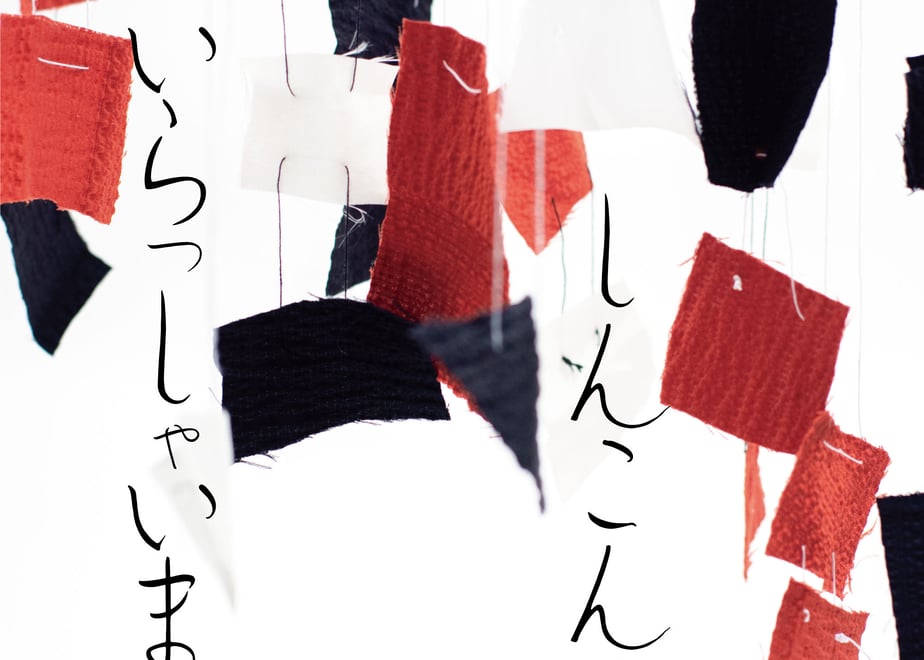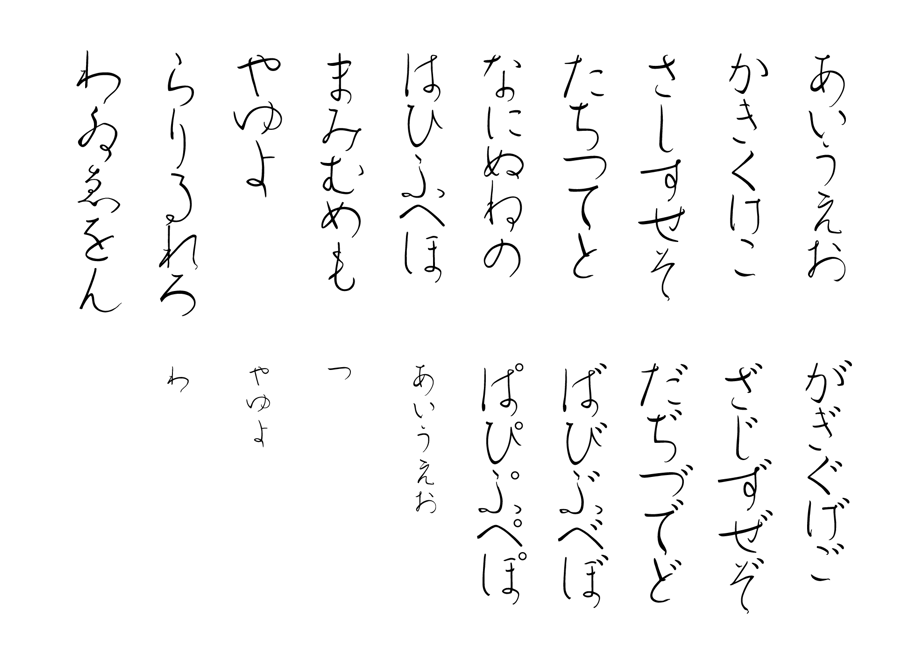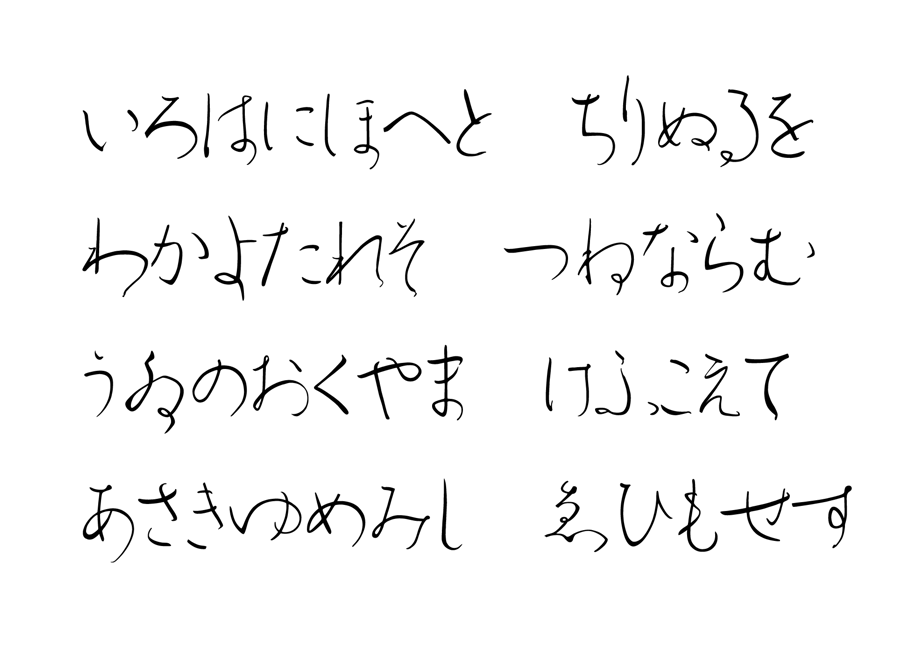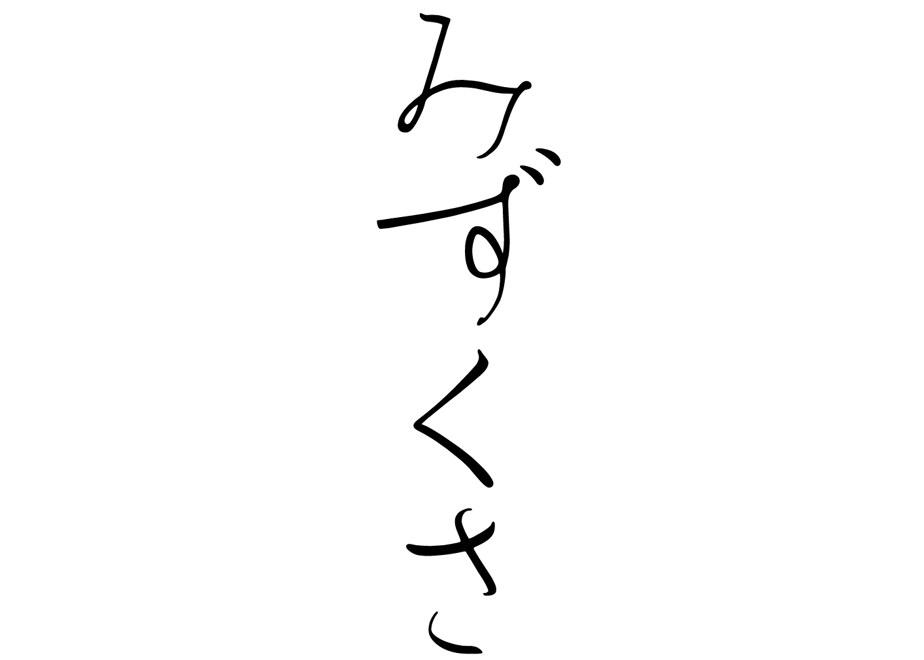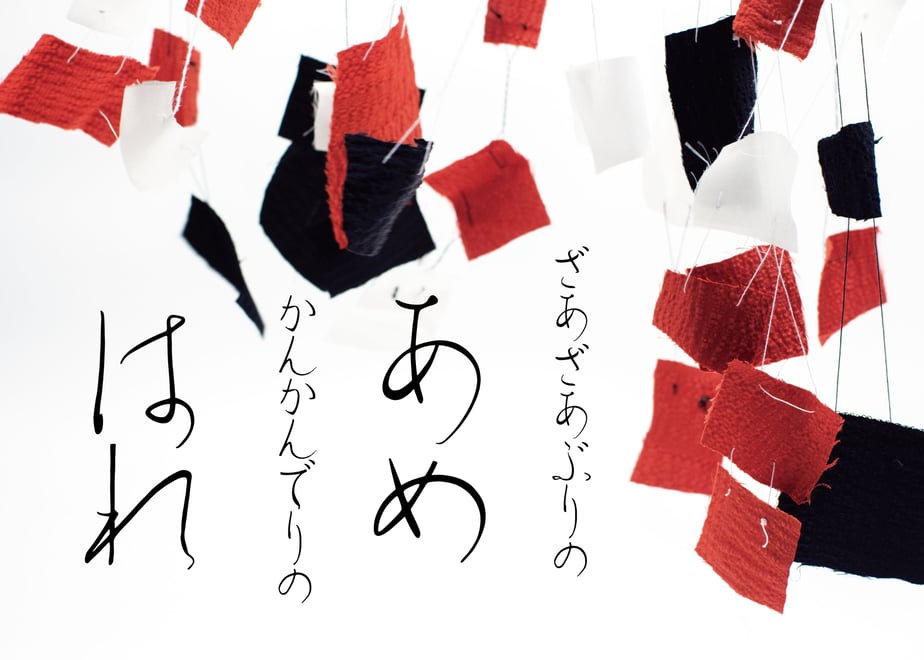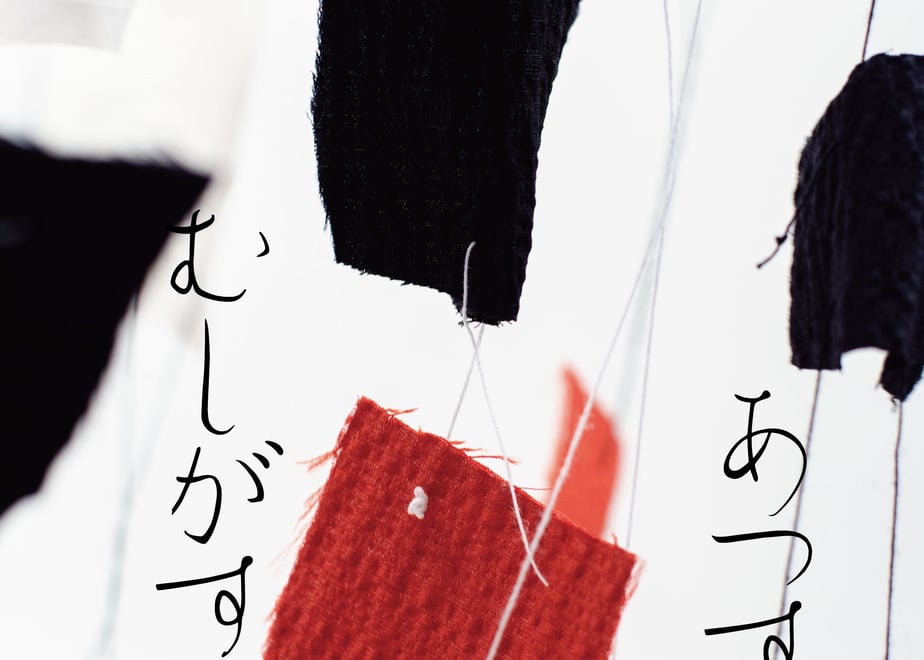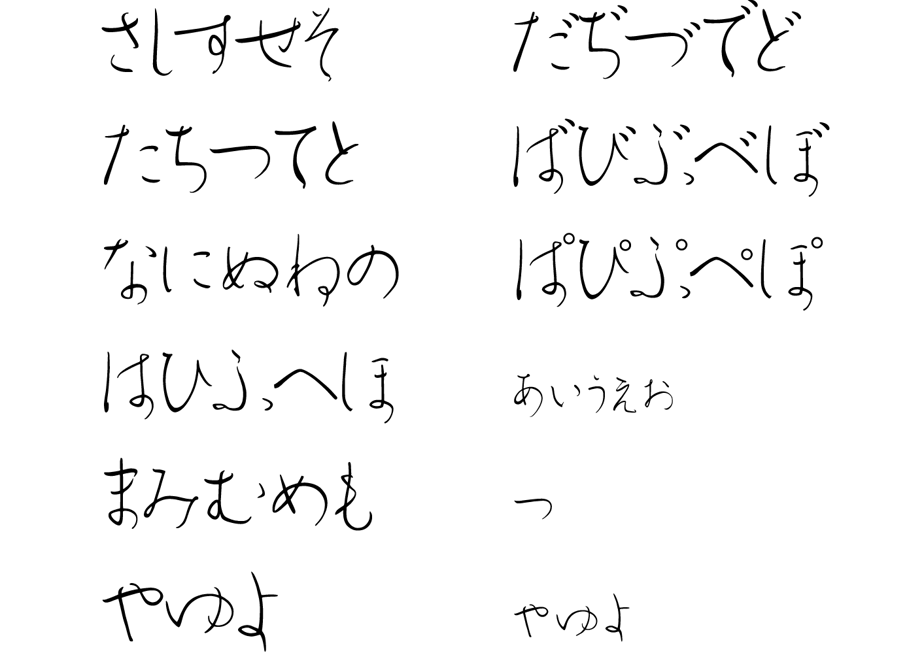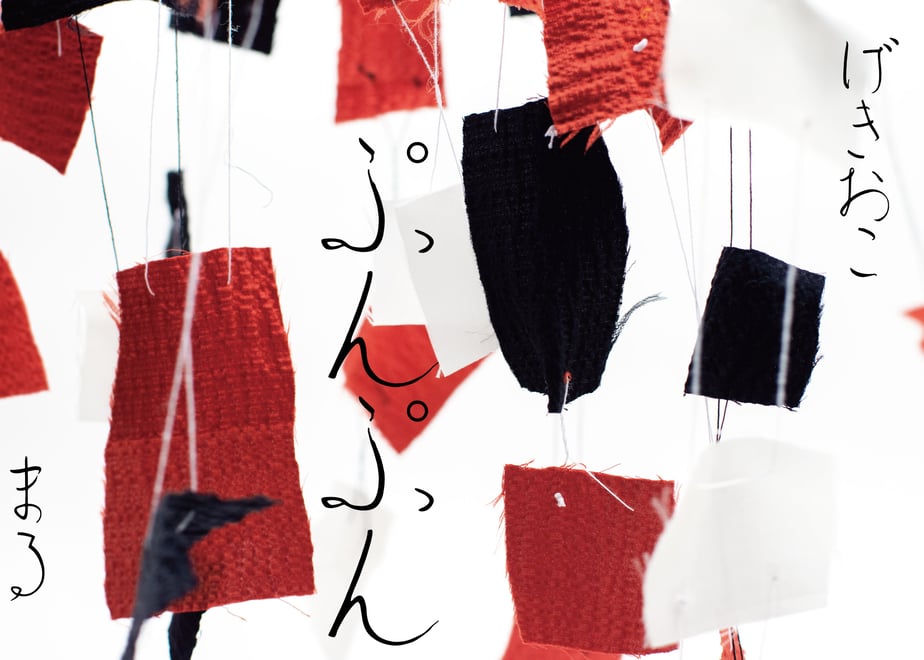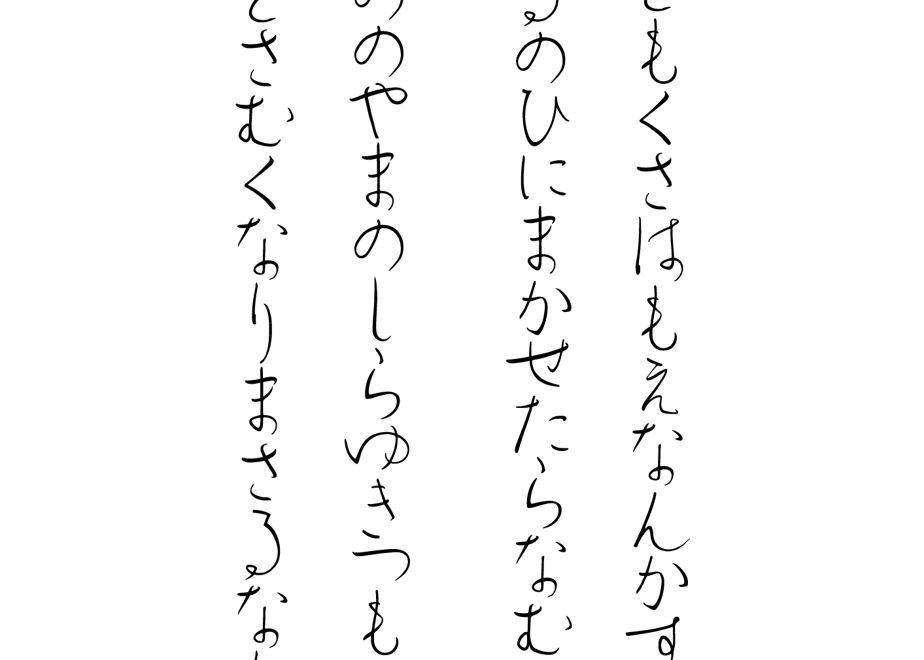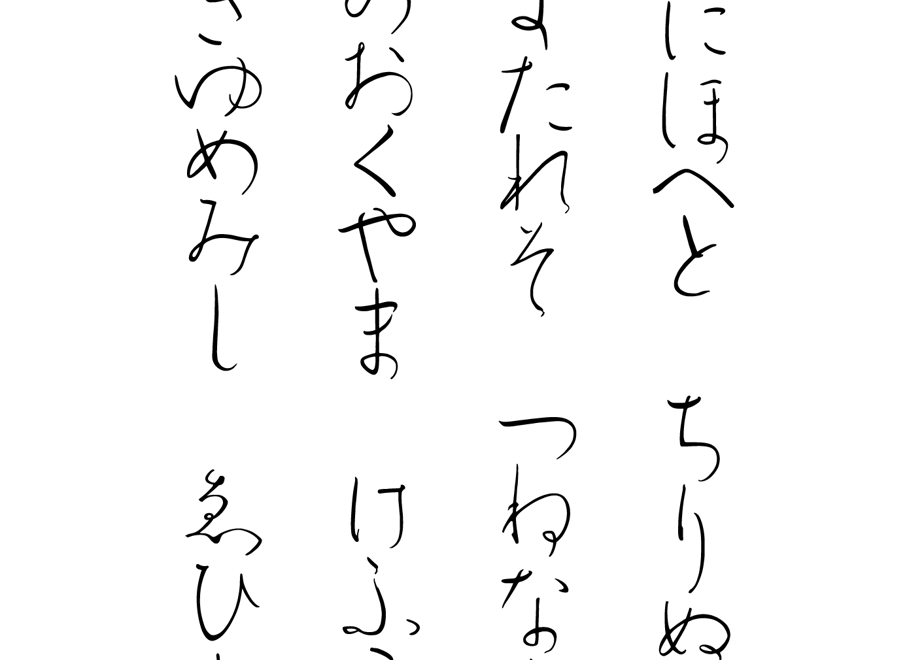
フォント:平仮名書体「みずくさ」
Hiragana is a voice-like design that extends its sleeves to hiragana as a sound, assuming that it was a male or female, or a tape that also records gender and personality. I kept in mind and reached the completion.
平仮名は声のようなもので男性であったり女性であったり、性別や人格をも記録するテープみたいなものであったのではないかという仮定の元、音としての平仮名に袖を伸ばした設計を心掛け、完成に至りました。